2020年的高考到现在来说基本上已经全部结束了,现在学生只需要等着各大高校的志愿录取了。我们都知道今年的这一届的高考是非同一般的,大部分考生们不仅面对在疫情期间复习的心理压力,还在高考之际遇见了各种各样的灾难和考验。
但是尽管如此,这一届的考生在高考中还是取得了非常好的成绩,所以我们肯定要从他们的身上找到成功的经验,并且好好地向他们学习。而我们首先要学习的就是这一届考生的“完美字迹”,下面我们就来看看2020年高考中两位状元考试中的字迹吧,基本上可以说是非常完美的,老师想扣分也无处可扣呀!
一、湖北省高考状元唐楚玥
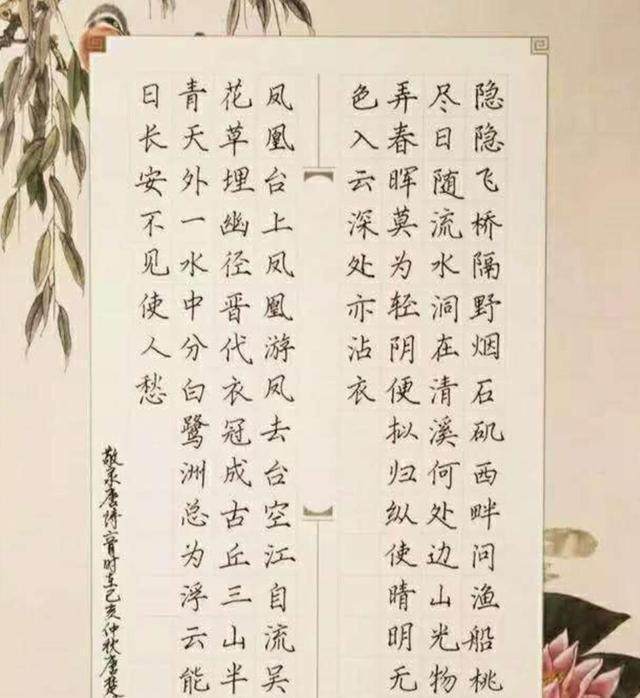
唐楚玥是湖北省理科高考状元,在高考中她取得了725分的高分,更重要的是她的语文成绩竟然高达146分,这简直让人难以相信,因为所有高中生都知道语文想要考高分的难度是非常的大,大部分都是主观题,学生很难写出与参考答案相似的答案。而这位湖北省高考状元竟然能够在高考中语文只扣4分,可想而知她写出来的答案与参考答案接近吻合,这除了她自己本身的实力以外,工整的字迹更是功不可没。
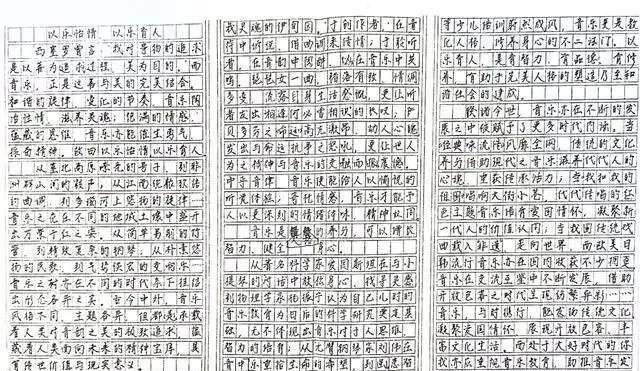
我们可以看到这就是唐楚玥平时所练的字,一笔一划非常的工整,由此可见她是多么的刻苦。我们从唐楚玥的答题卡也可以看到卷面是非常的整洁,作为阅卷老师碰到这样的试卷心情一定是非常的愉悦,从而也很难再去扣其他的分数了。
二、江西省高考状元尹天骥
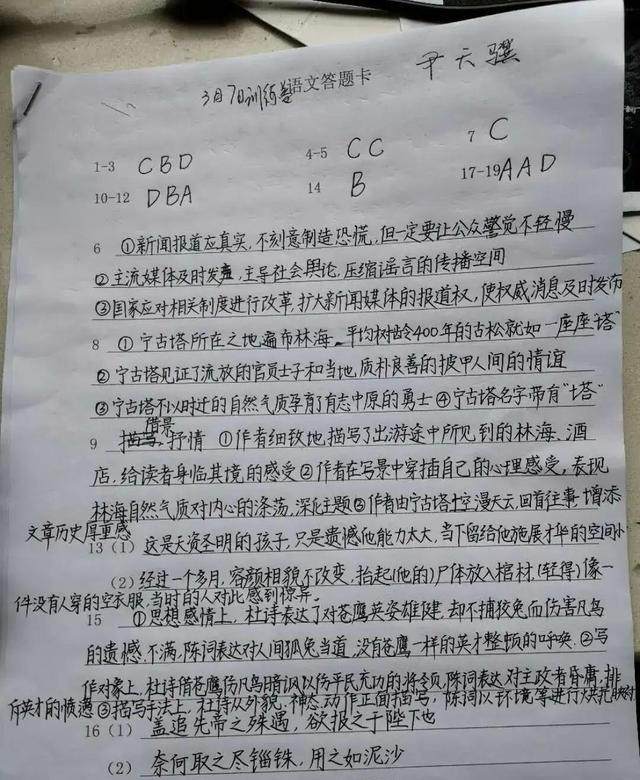
尹天骥同学平时就很喜欢练字,他的字迹非常的饱满同时也非常的规矩,让人看起来感到非常舒适。下面这张图是尹天骥同学在平时做作业时候的情况,我们可以看到这些字体是工工整整并且非常的清晰,简直是“完美”了,很多网友也夸赞他写的字就像“印刷版”。
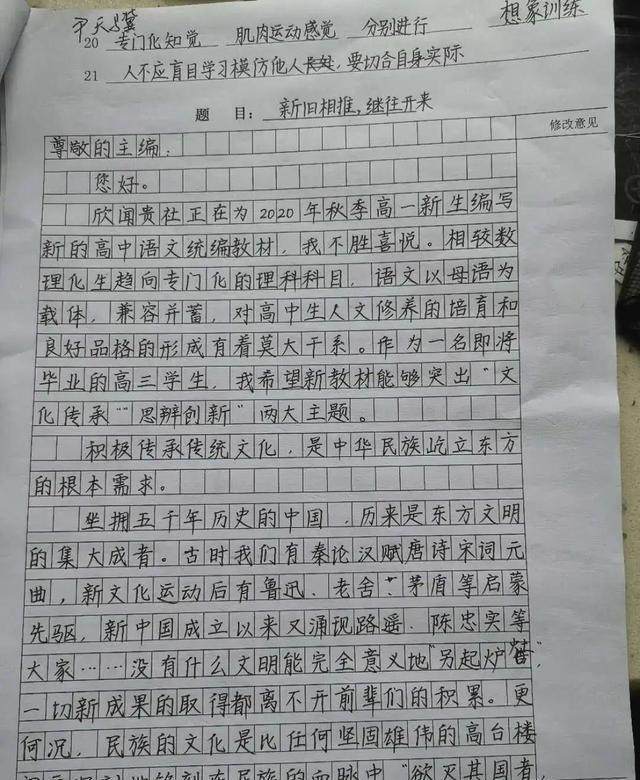
而由于长期以来的练字,尹天骥养成了非常好的写字习惯,在高考中也理所当然地写出了非常整洁的字迹,这份试卷的图片是由尹天骥父母上传到网络上的,随后就引起了网友的羡慕,“赏心悦目”便是如此的感受呀!
所以说要是想在考试中取得一个不错的成绩,除了平时要学习好课本知识之外我们还应该努力去把字练好写好,能够写得一手好字的话,那么对于语文考试甚至是文科生的所有考试都将是有着非常大的好处的!大家快趁着假期行动起来吧!正如大家所说的见字如见人,拥有一副好的字体,能让别人对你刮目相看。